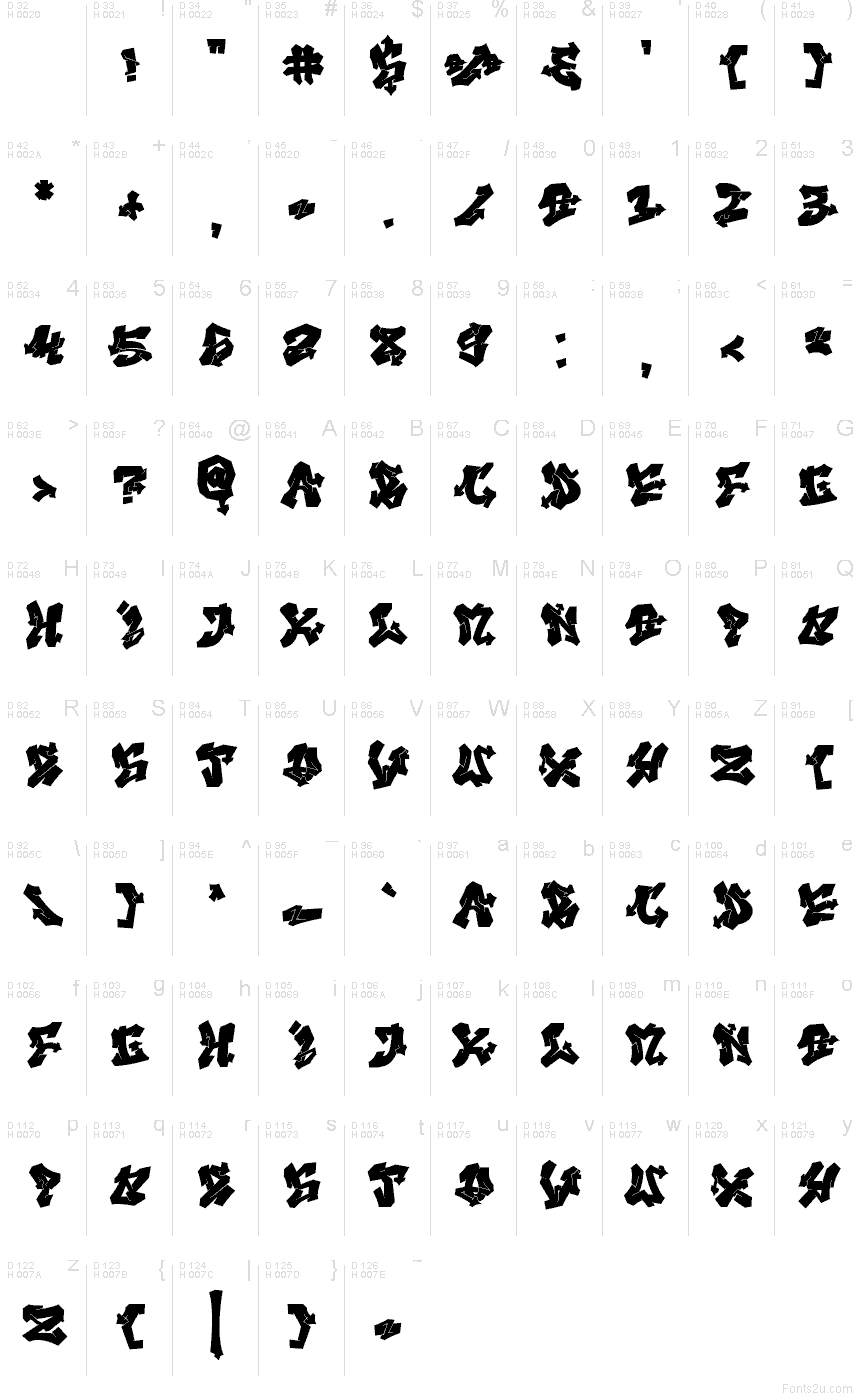
Il font Nightclaw Vandal Solid, firmato da Muhammad Panji Ramdhani e Ferbiya Rahmat di Cikareotype, colpisce come un blackletter frantumato e spruzzato con inchiostro denso: blocchi angolari, tagli netti e un ritmo serrato che evoca atmosfere sia medievali che street. Parte della famiglia Nightclaw Vandal, è un font graffiti gratuito con una silhouette pesante e solida che mantiene tutta la sua grinta anche nei titoli più piccoli.
Utilizzando Nightclaw Vandal Solid, darai un mordente immediato a loghi streetwear, copertine di album, poster di skate, titoli per videogame, miniature horror, volantini per eventi ed etichette per merchandise. Per preservarne la leggibilità, concedigli il giusto respiro e abbina questo font gratuito a una geometric sans pulita per i testi di supporto.